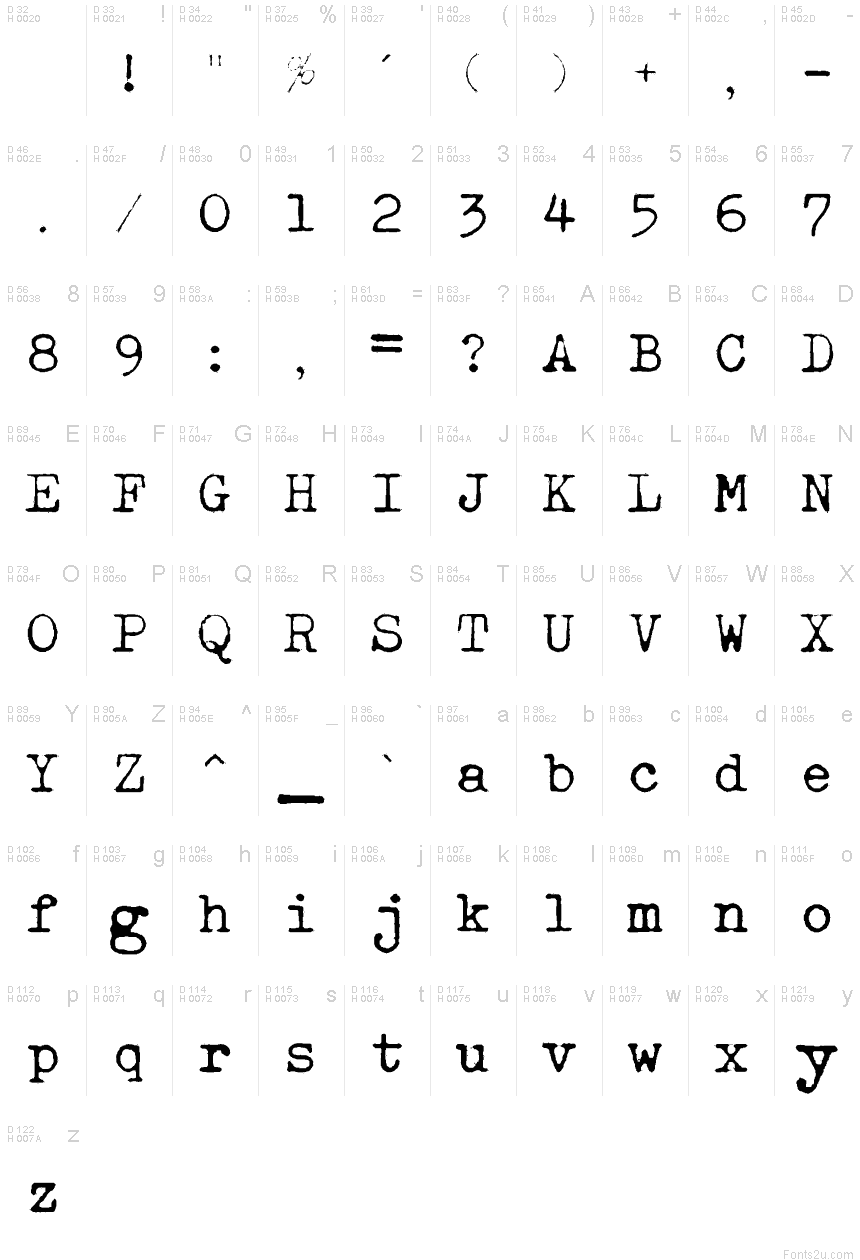
Esat Hoxha to darmowy krój szeryfowy w stylu vintage z efektem erozji. Litery wyglądają, jakby zostały wyklepane na starej maszynie do pisania i lekko rozmyły się na szorstkim papierze – masywne trzony, poszarpane krawędzie i ślady tuszu tworzą surową, analogową atmosferę. Odstępy pozostają zaskakująco równe, dzięki czemu uzyskujesz cały ten grunge’owy, historyczny klimat bez utraty czytelności.
Dzięki Esat Hoxha nadasz plakatom, horrorowym tytułom, zinom, okładkom albumów, grafikom do escape roomów czy okładkom książek autentyczny, zużyty charakter rodem ze starej drukarni. Ten darmowy font najlepiej sprawdza się w większych rozmiarach, gdzie surowa tekstura może naprawdę wybrzmieć. Dla tekstów pomocniczych warto zestawić go z czystym, nowoczesnym krojem bezszeryfowym, który zapewni dobrą czytelność.